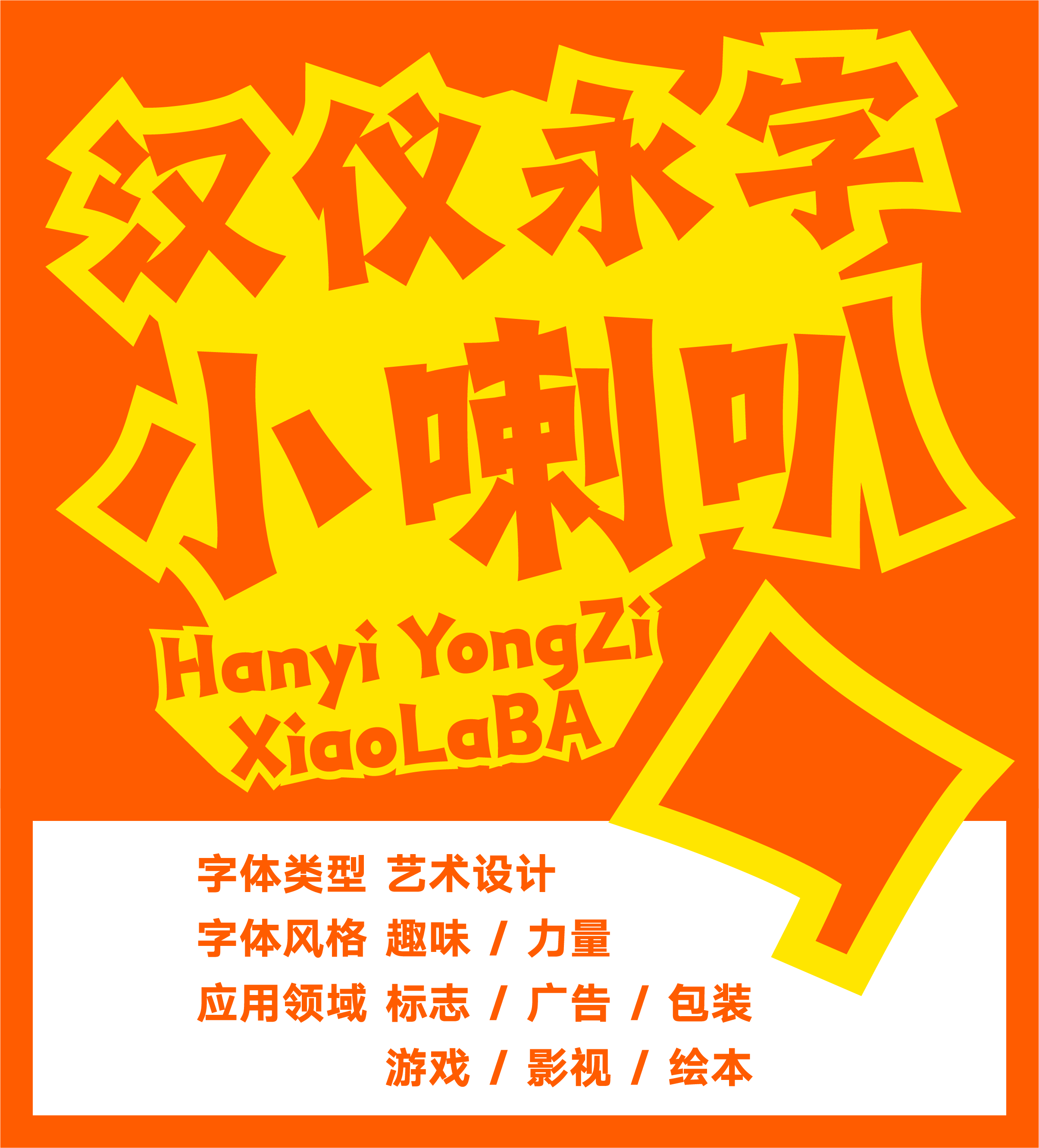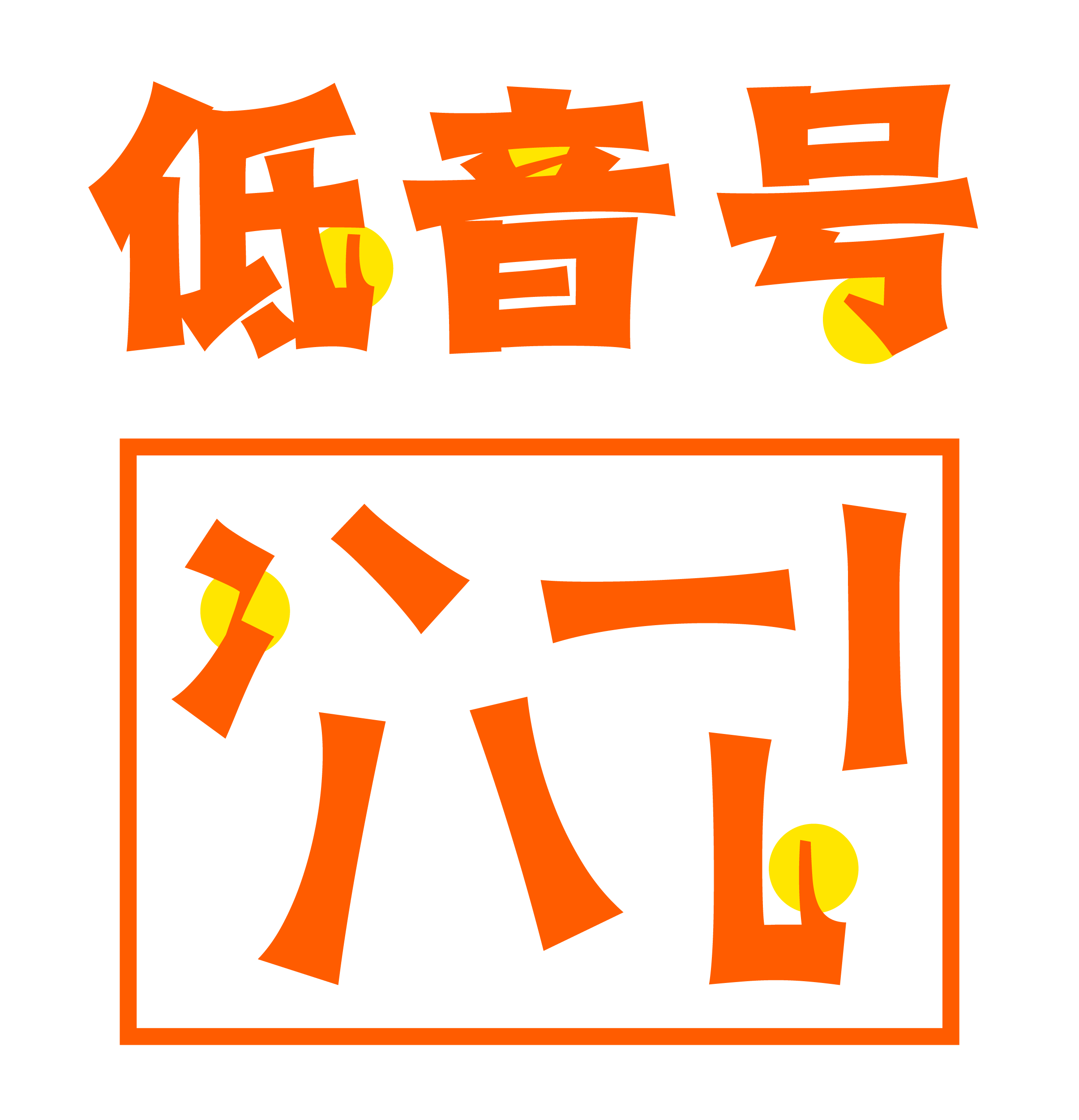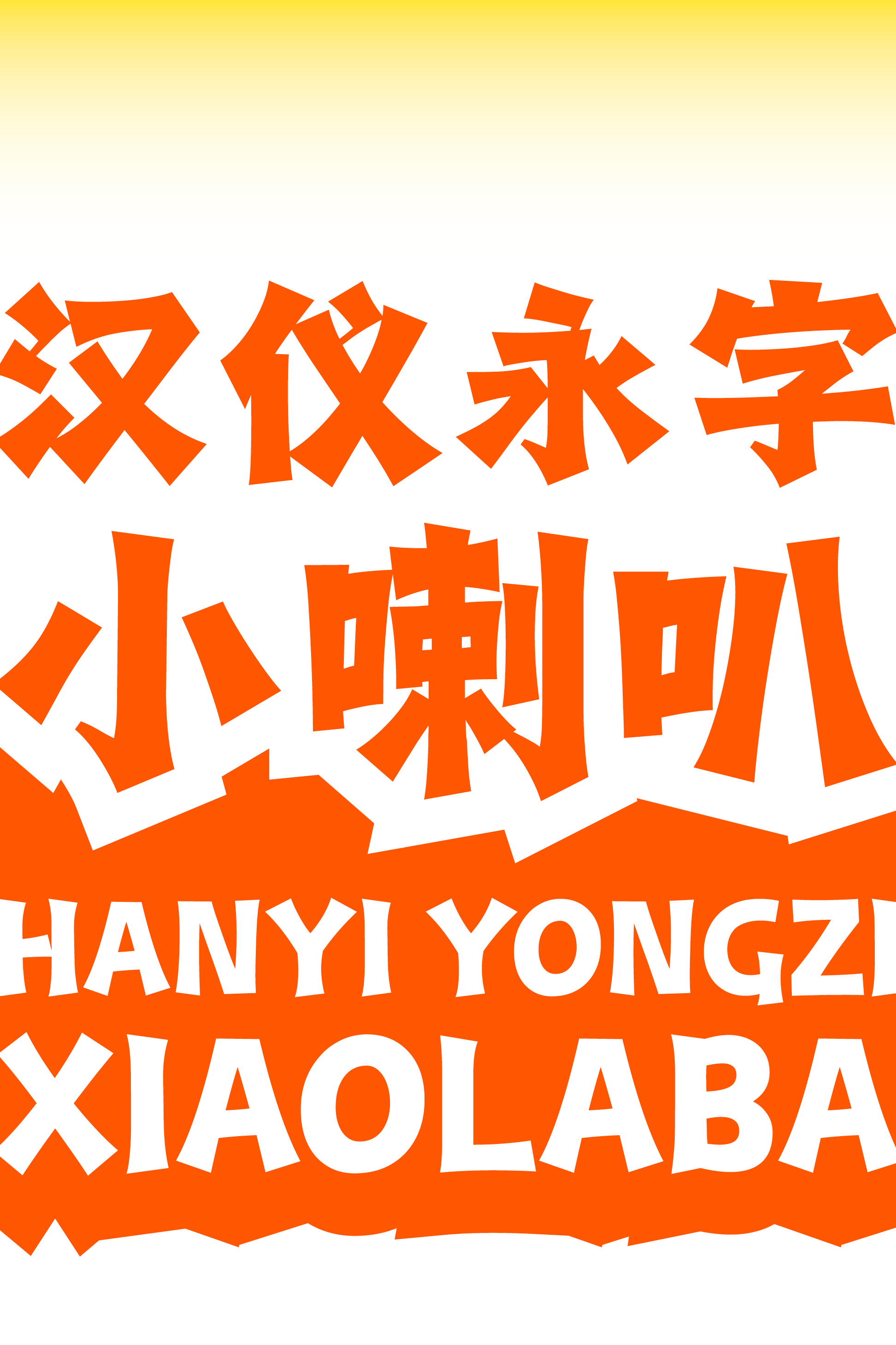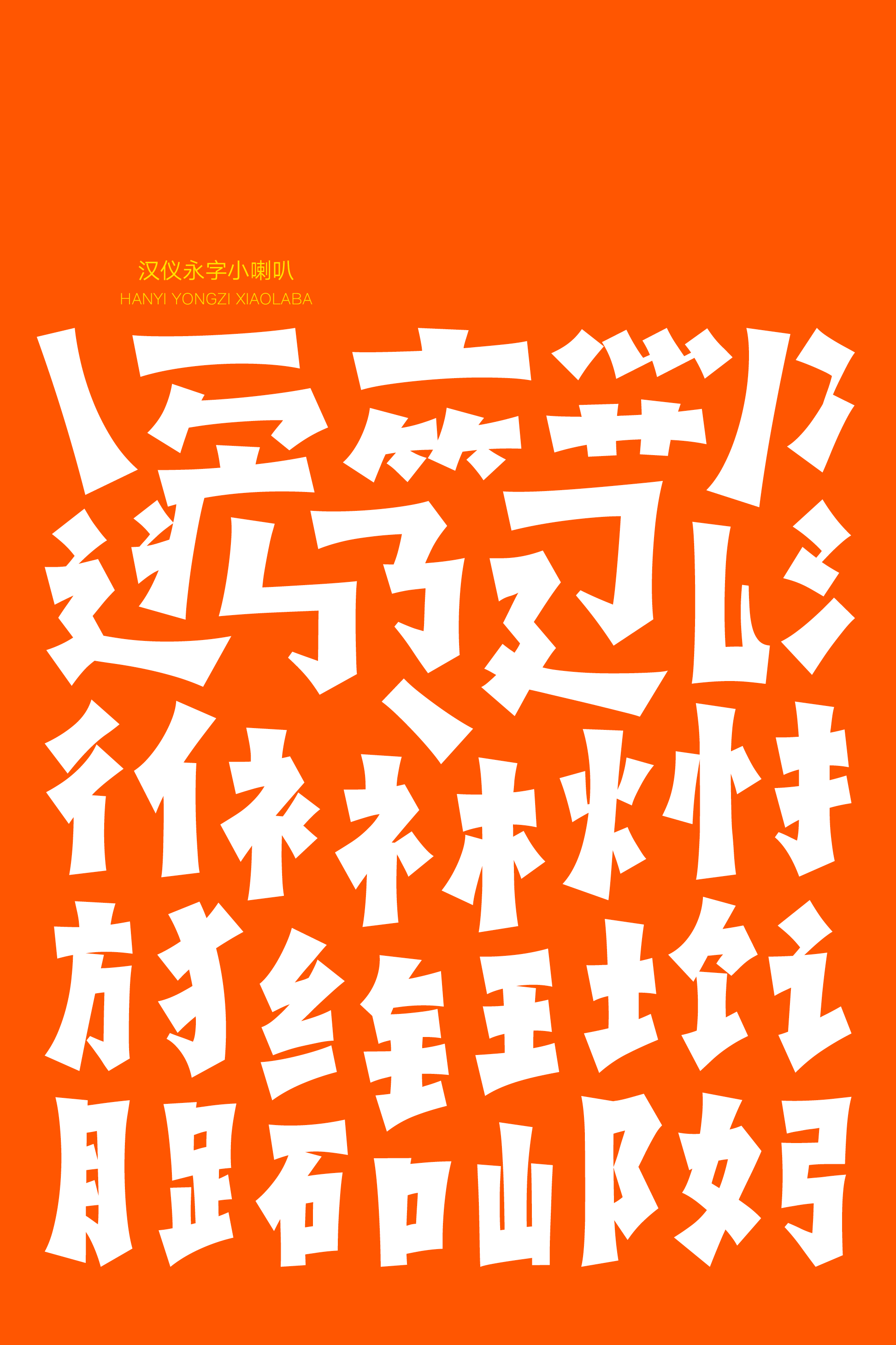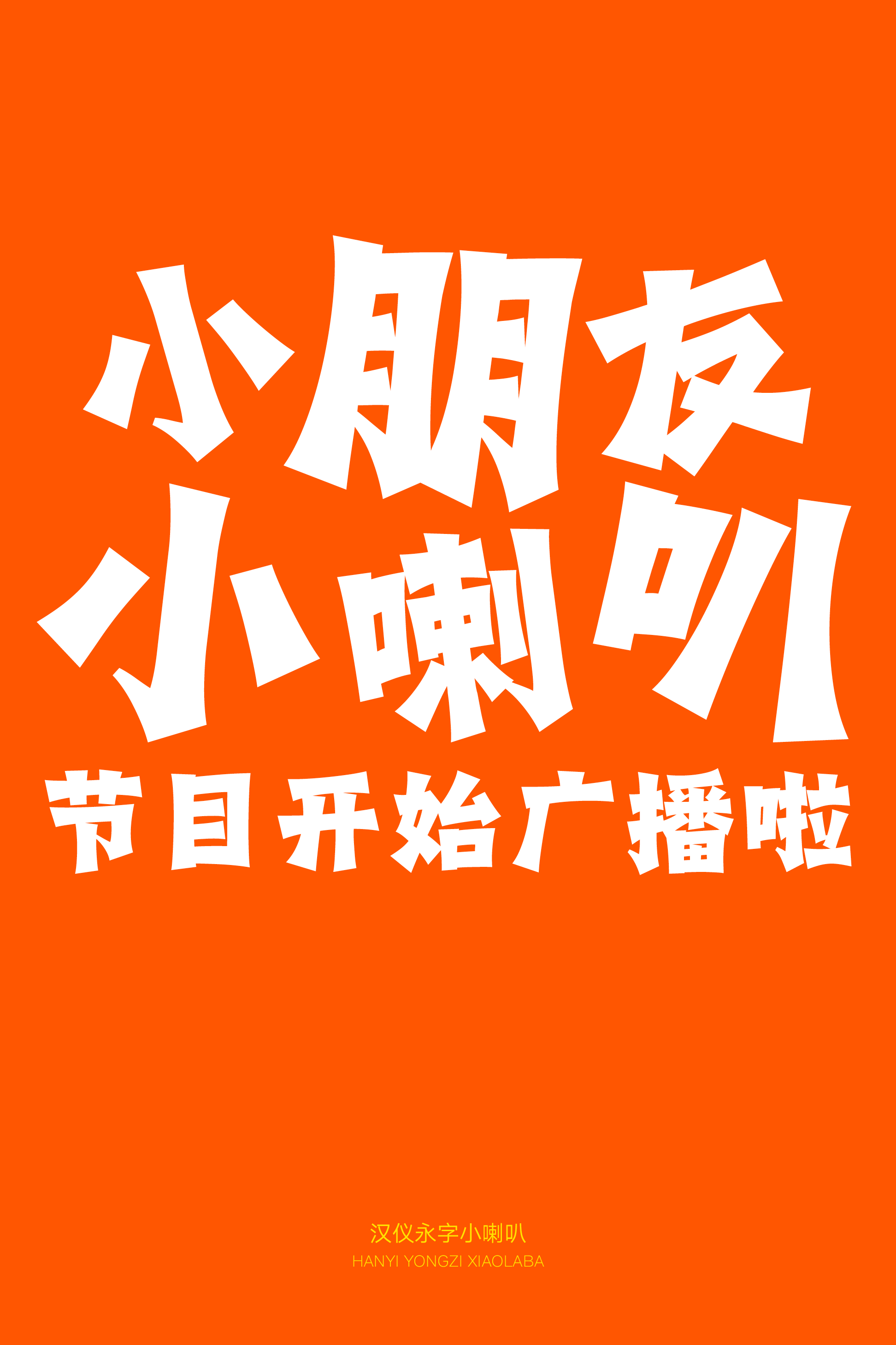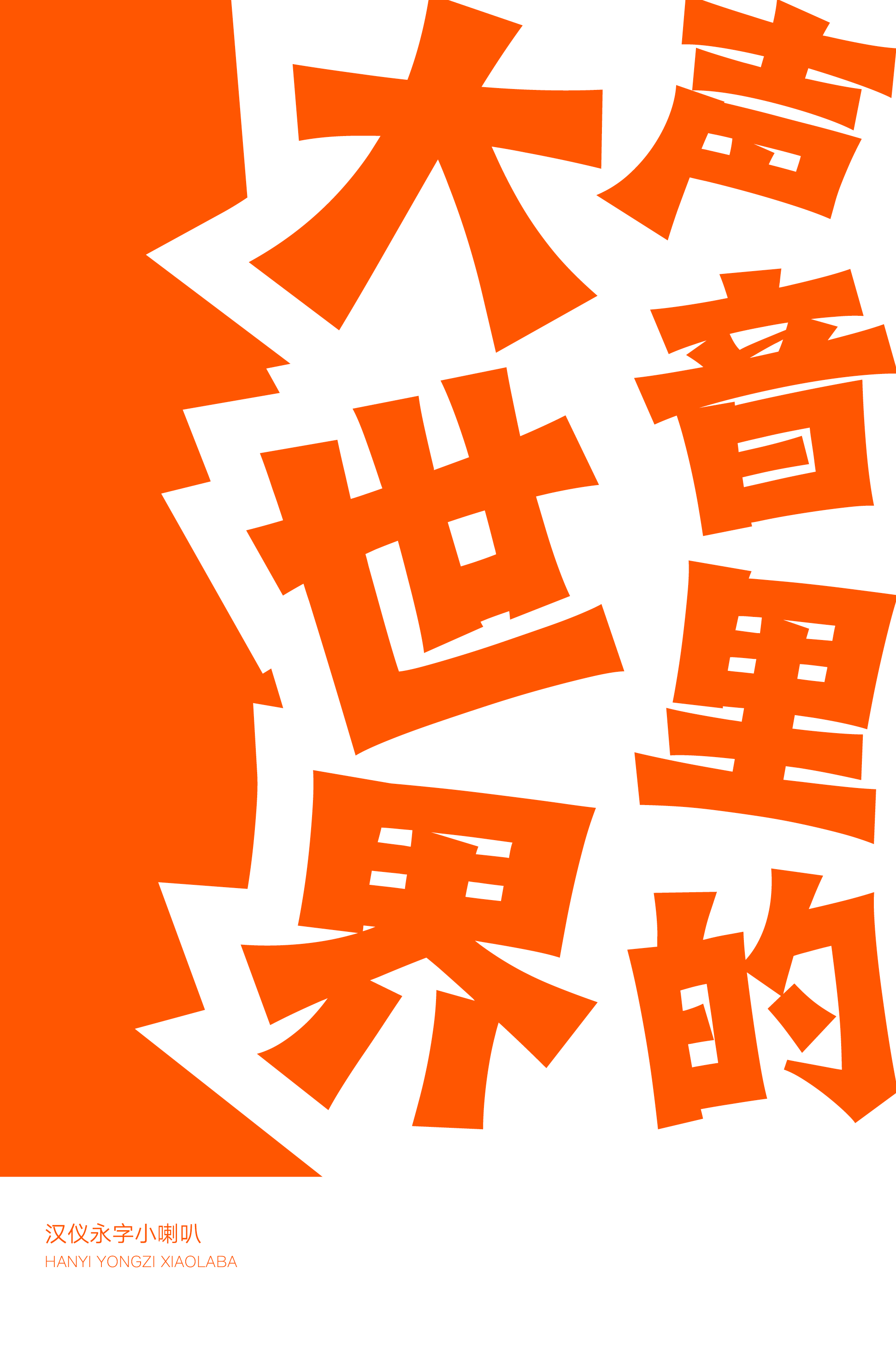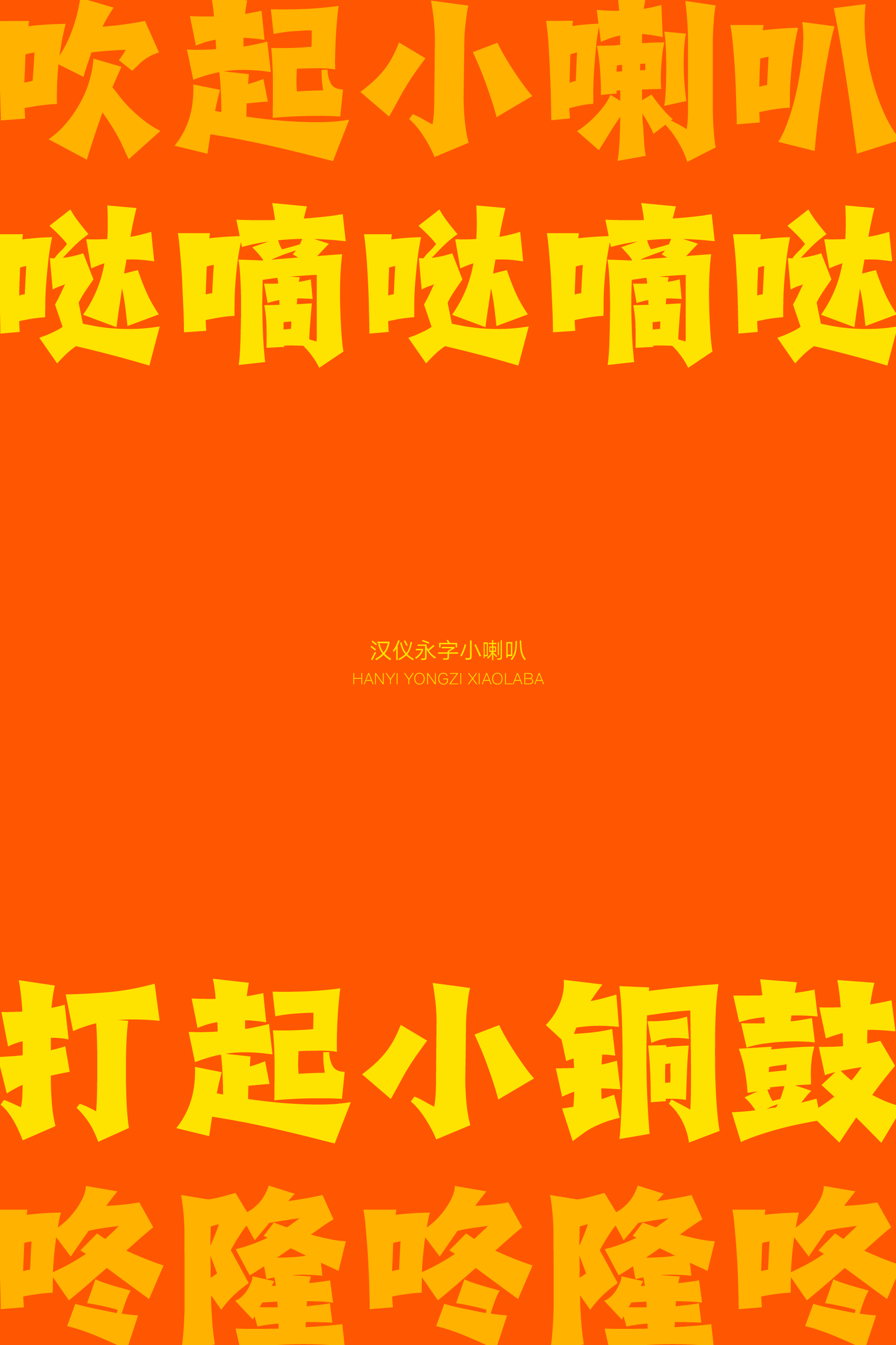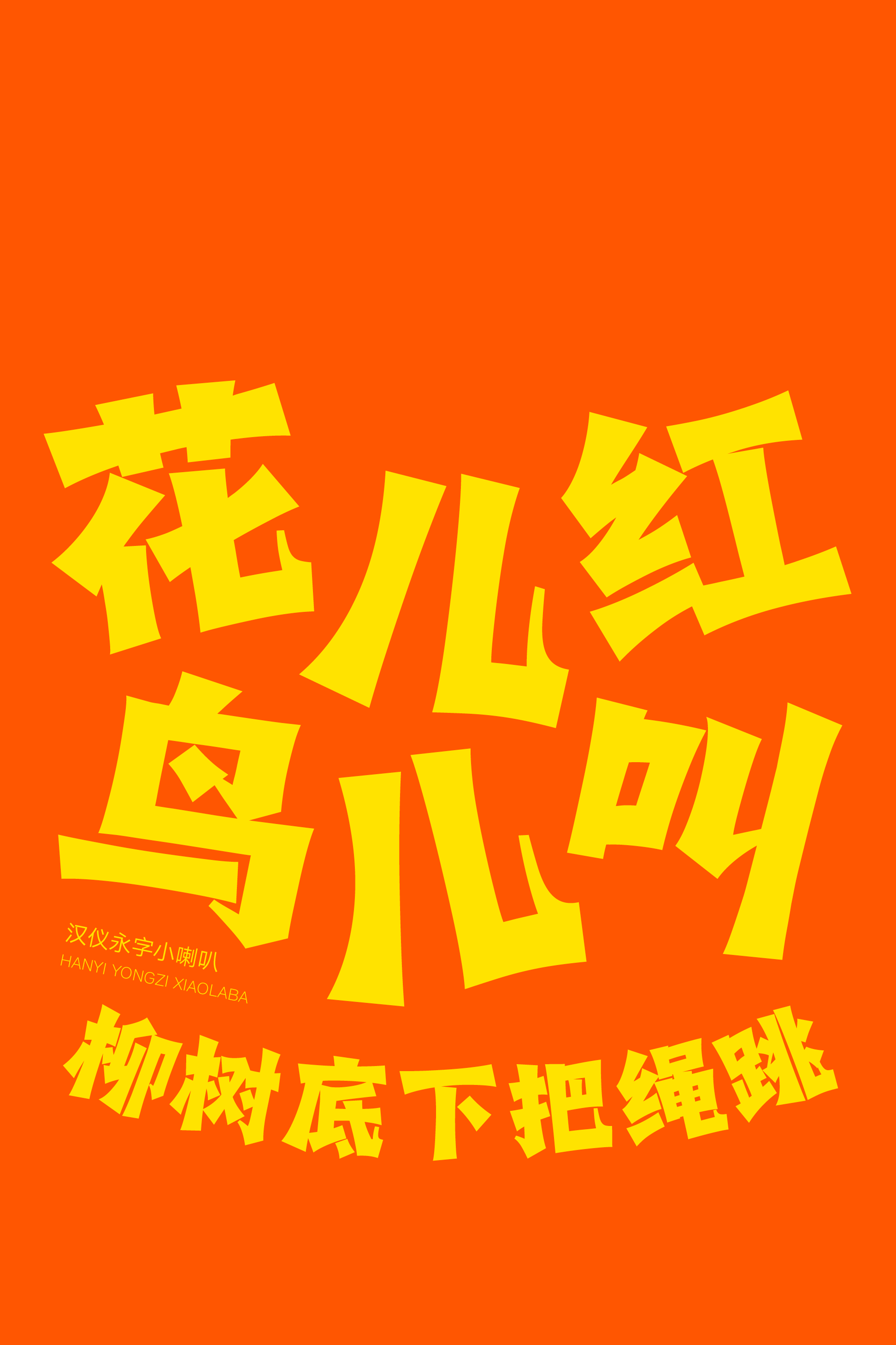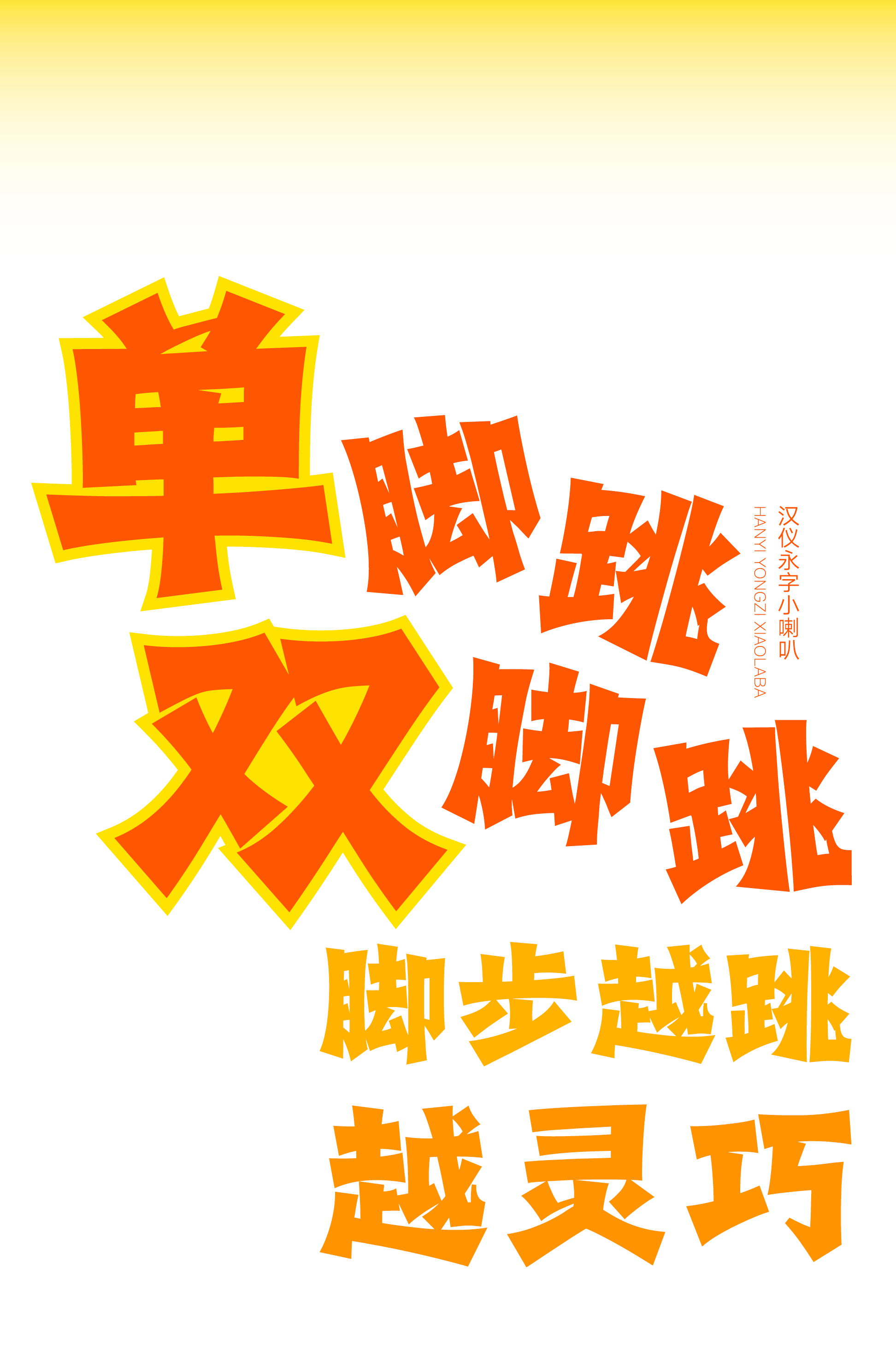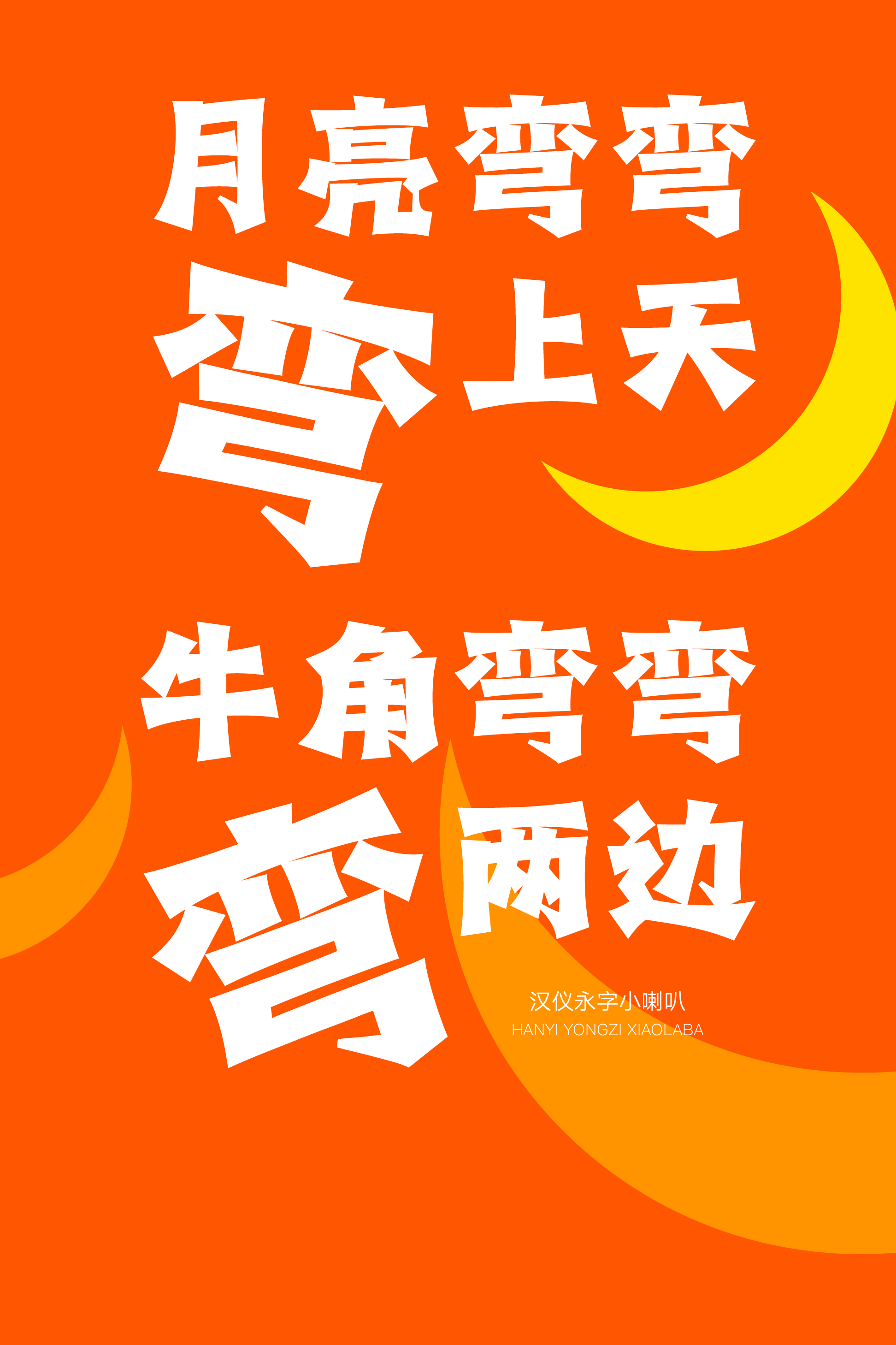
汉仪永字小喇叭
“嗒嘀嗒、嗒嘀嗒、嗒嘀嗒——嗒——嘀——;小朋友,汉仪永字小喇叭开始广播啦!”
由永字社创作的「汉仪永字小喇叭」,以黑体作为基础,夸张放大了喇叭口的特征,配合细尖有力的钩画和部分笔画之间的连带,形成了趣味十足而有张力的视觉效果。这款风格鲜明的创意标题字体音量大,用于品牌标识、广告包装十分引人注目,用于影视综艺、游戏娱乐、童书绘本趣味横生,活泼可爱。
汉仪永字小喇叭标志性的特征是夸张放大的喇叭口,笔画两端外放的造型。
字形中间收紧,向外扩张,整体有“音量放大”的视觉效果。
在粗重有力的笔画之间,细尖的钩画和部分笔画之间的连带丰富了细节。
西文部分同样强调了笔画的外放造型,中西文匹配的小喇叭广播活泼有趣。